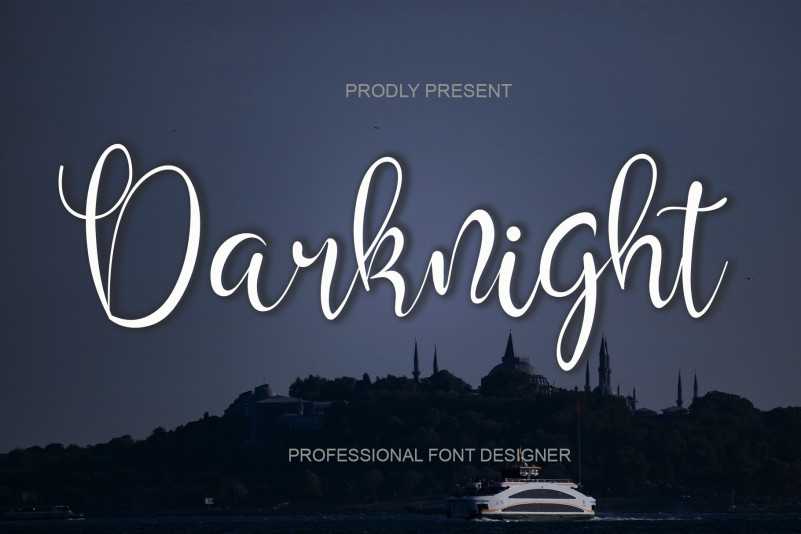
Esta é uma linda fonte escrita à mão que transmite ao longo do tempo e sofisticação. É a escolha perfeita para criar logos impressionantes, identidades visuais e citações. Cada letra tem um toque único e belo, tornando sua criação viva e vibrante. A Kateengciu nos presenteia com esta fonte de escrita à mão que capta o espírito criativo e a elegância da arte do desenho. Quebre o estereótipo e personalize seus designs com essa incrível fonte, perfeita para criar uma identidade visual única ou transformar suas citações em algo inesquecível. Darknight Font é ideal para designers que buscam mais que apenas um recurso gráfico: procuram um elemento de personalização que dê vida à sua criação.